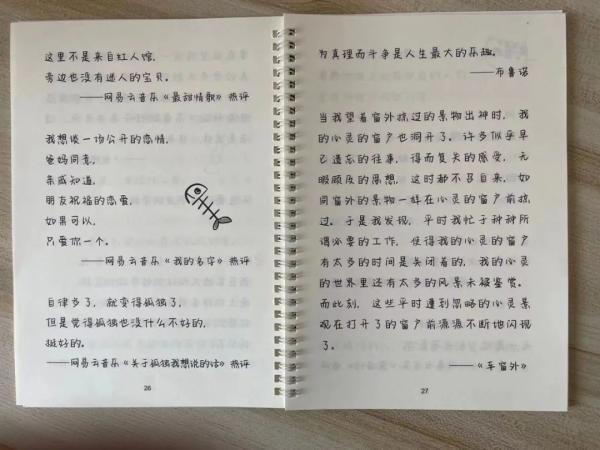
在很多中学生的作业本上出现了一种字体,因圆润、小巧,深受女同学的追捧,它还有一个好听的名字叫做“奶酪体”。3月22日,山西晚报记者在采访中发现,虽然受到学生青睐,但“奶酪体”并不被老师看好。有的同学表示,曾因为用“奶酪体”,被老师误判为错别字扣分。
什么是“奶酪体”呢?
22日下午,山西晚报记者在太原市杏花岭区一所学校了解到,这样的字体在电脑上的艺术字范畴里经常可以看见,字体小巧圆润,而且写出来俏皮又不失秀气,整篇分布在作业本上看上去非常整齐,因此深受女同学的追捧。
一位上初一的女生告诉山西晚报记者,她们班有一半的人都在使用这样的书写方式,并且这样的字体还可以买到练习的字帖。同学中有不少人都在对照字帖进行练习,她也会在课余时间练习书写这种字体。还有一位同学说,自己从小学六年级开始就用这样的字体,她还拿出自己的作业本让山西晚报记者看。果然,她的作业本字迹秀气,整体工整清丽,的确非常赏心悦目。
然而,这样的字体却并不被老师欣赏。一位同学说,因为这种字体小巧圆润,因此很多的笔画略有简略,比如“舍”字下面的“口”,书写时基本上是一个三角形。还有一些笔画的“钩”也被省略了。因此一些老师会认为这是错别字而扣分,她之前就因为这样的问题,被老师扣掉5分的书写分,还专门将不规范的字当成错别字被老师圈了起来,之后她就不再使用这样的字体了。
那么在老师眼中,这样的字体到底有哪些弊端呢?
从事语文教学多年的苏玉莹老师告诉山西晚报记者,“奶酪体”是一种新型的字体,还没有一个准确的定义。这种字体给人的感觉就是工整清晰还不失可爱,但是很多的字为了俏皮就缺少了笔画。对于学生来说,使用这种字体并且用于考试是非常吃亏的,因此并不建议同学们广泛使用。苏老师还说,凭借自己当老师这么多年的经验来看,在考试中,使用宋体字更加容易得到电脑的认可,也更容易获得高分。因为宋体字本身笔画清晰,字迹工整,又是电脑上被默认的字体,所以建议学生可以多加练习和书写。